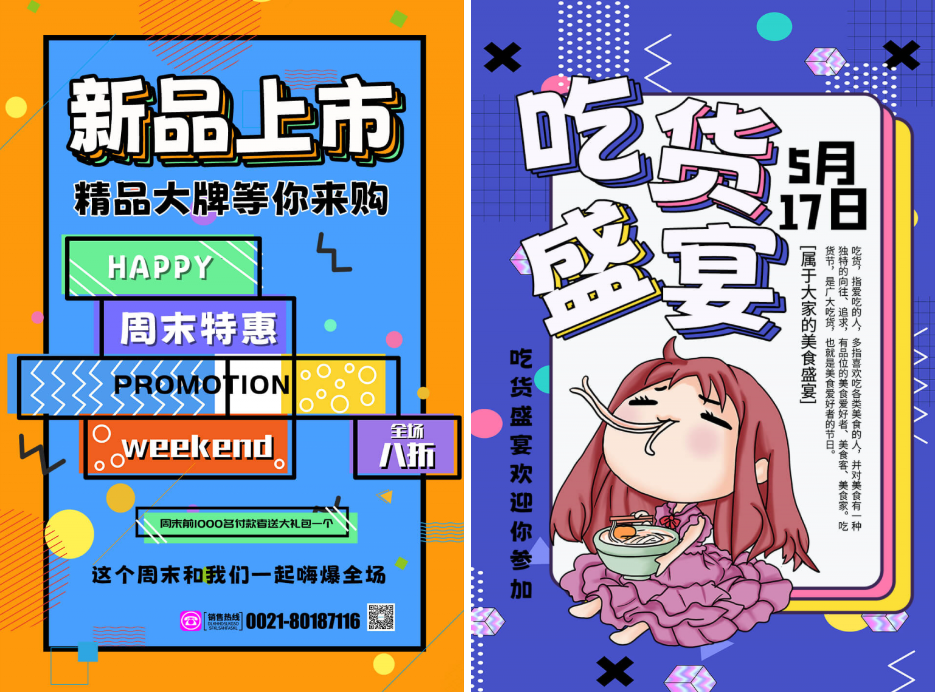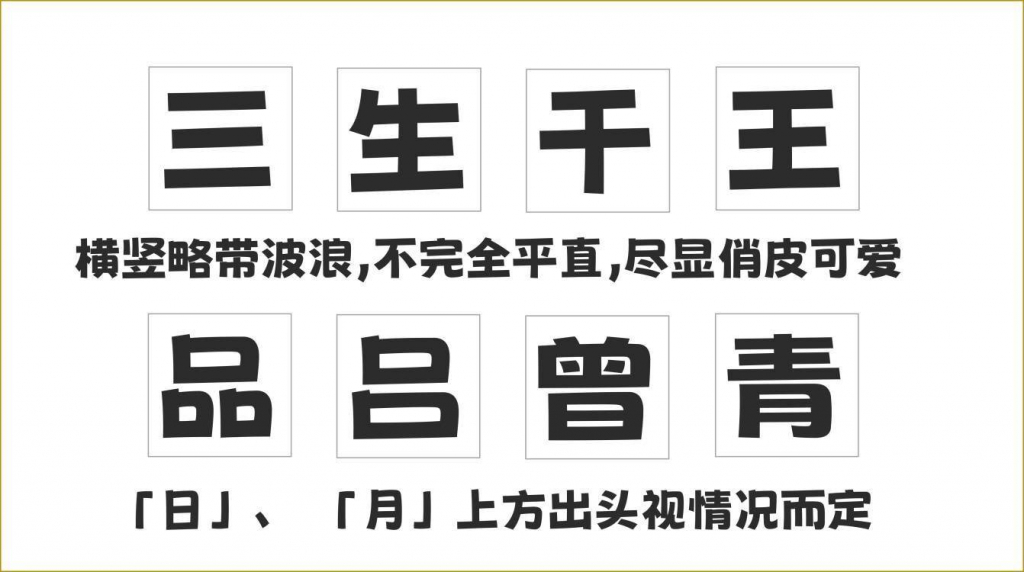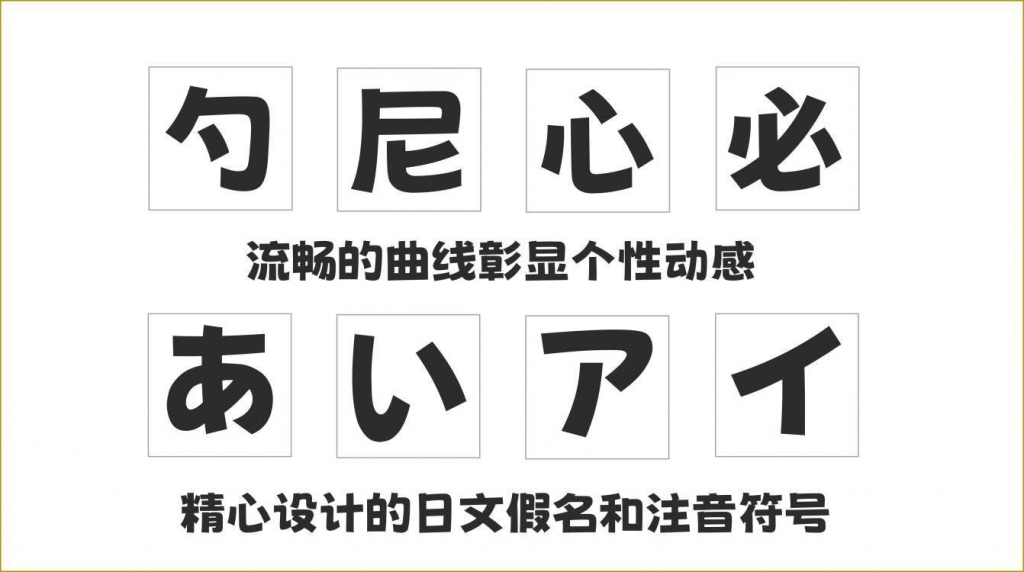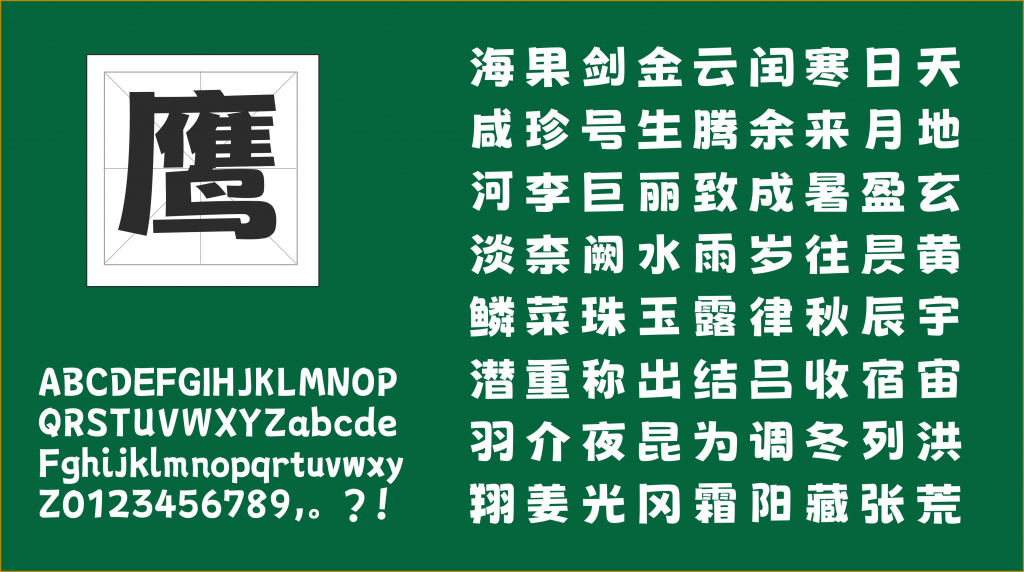
荆南波波黑(Kingnam Bobo)是由荆南字坊(光谷字造创意有限公司)推出的一款风格俏皮可爱的免费可商用卡通美术字体。
这款字体以 POP 艺术为灵感,融合手绘马克笔质感,笔画横竖略带波浪,不完全平直,但粗细均匀,在各类尺寸下均能保持清晰辨识度,适合标题设计和细节装饰,比如儿童文创产品包装、活动海报主标题、短视频封面、可爱风格的品牌 LOGO、卡通主题 PPT 标题等。
- 截至最新版本(V1.80),补全了方正简繁、日文STD、部分香港常用字及异体字。